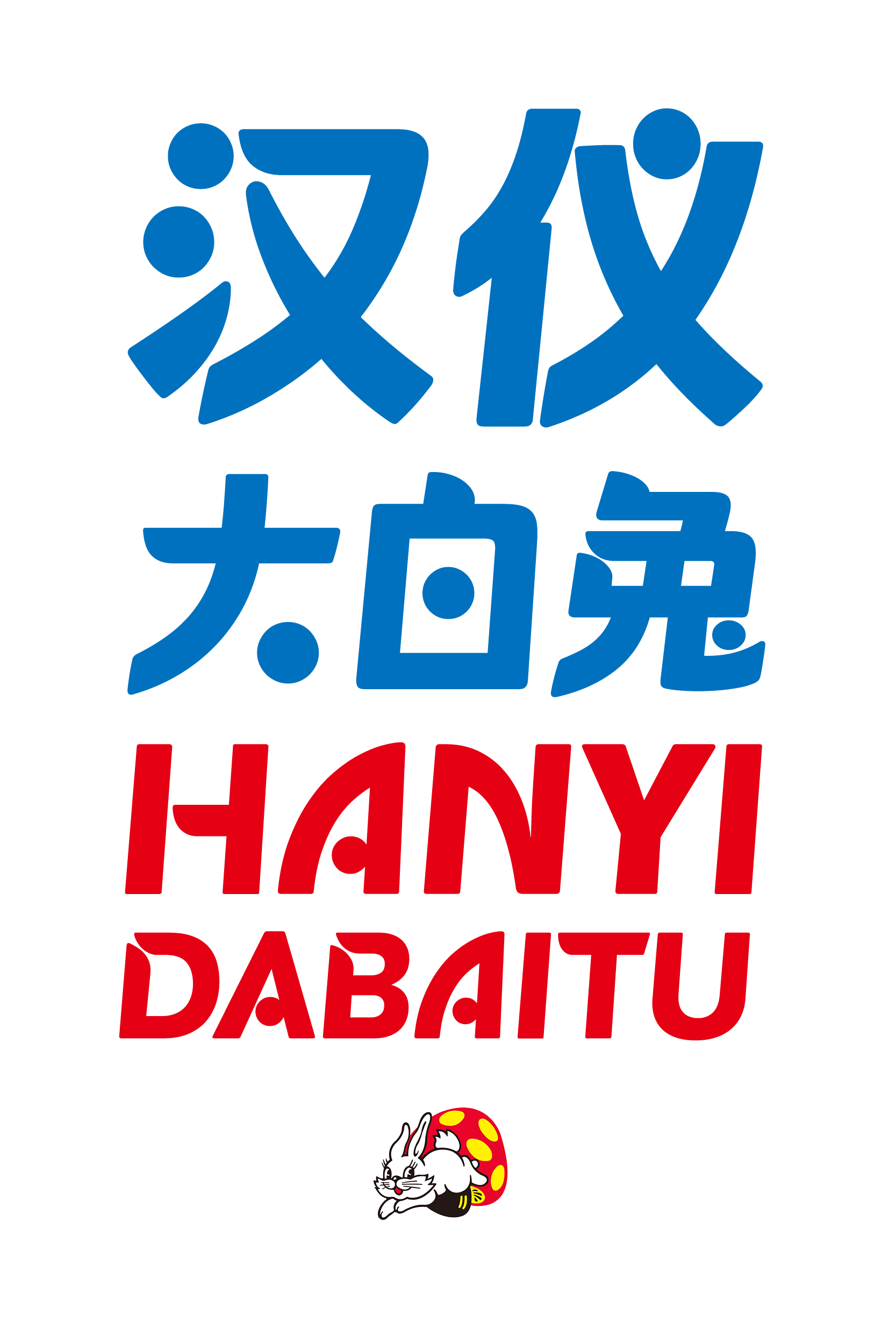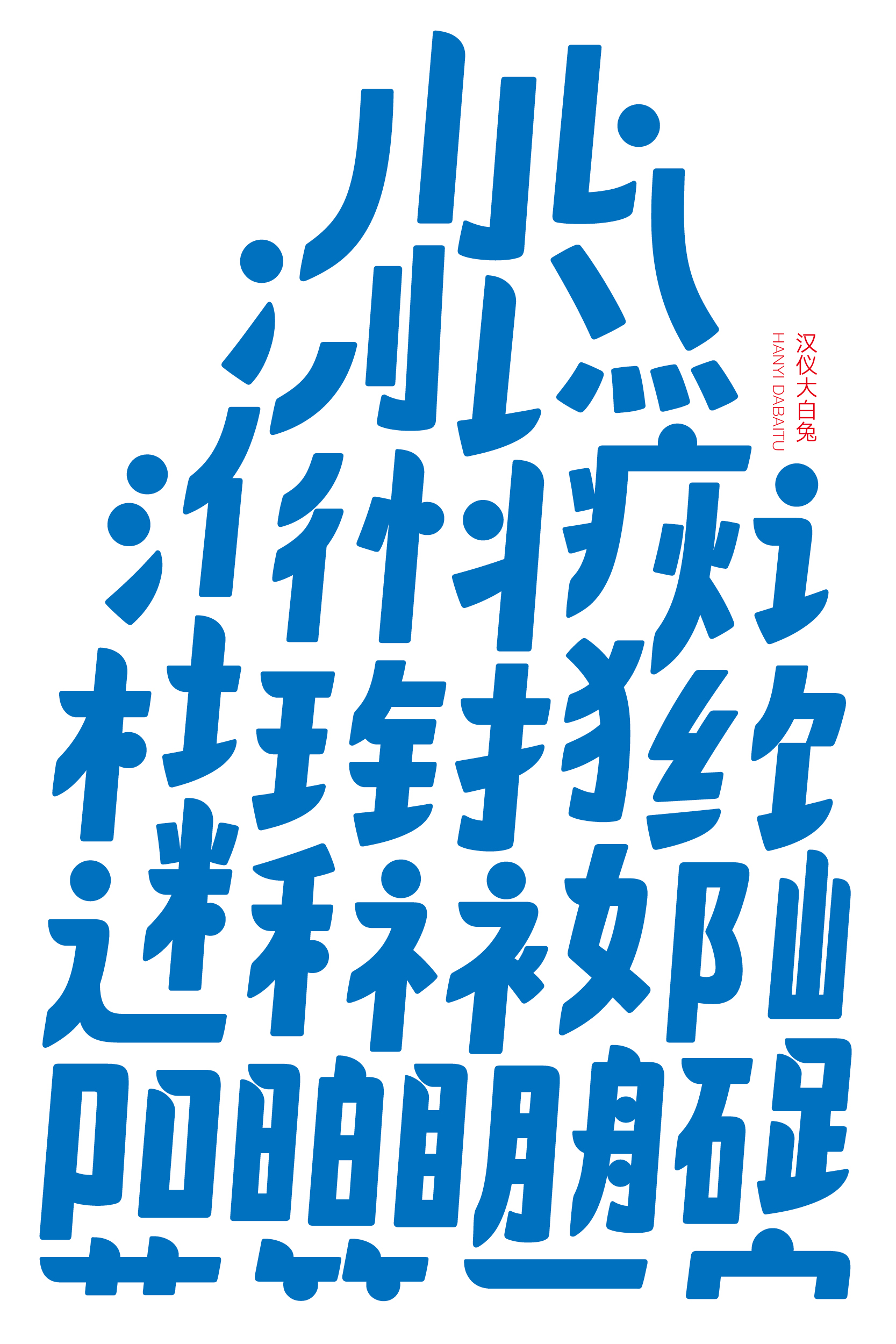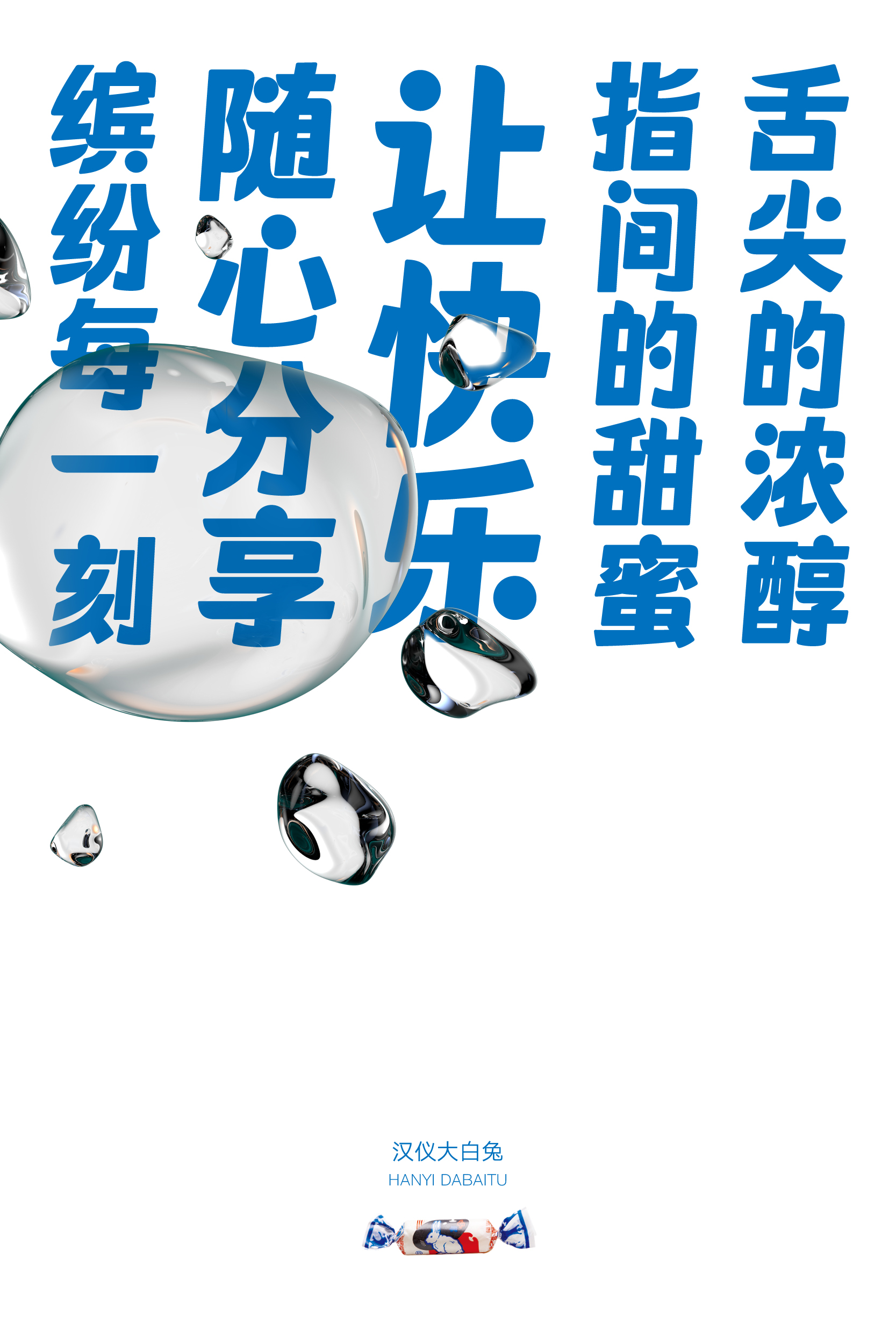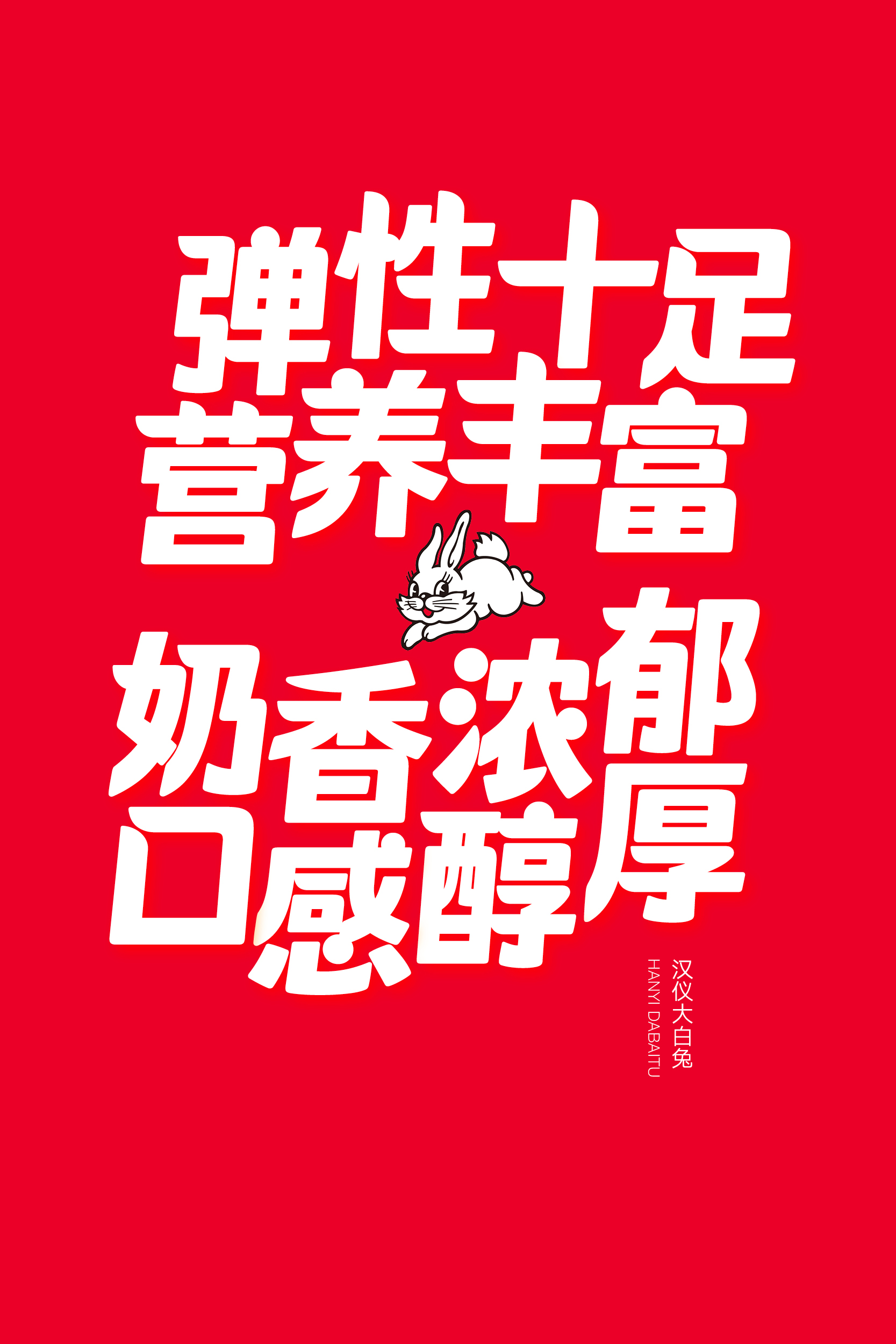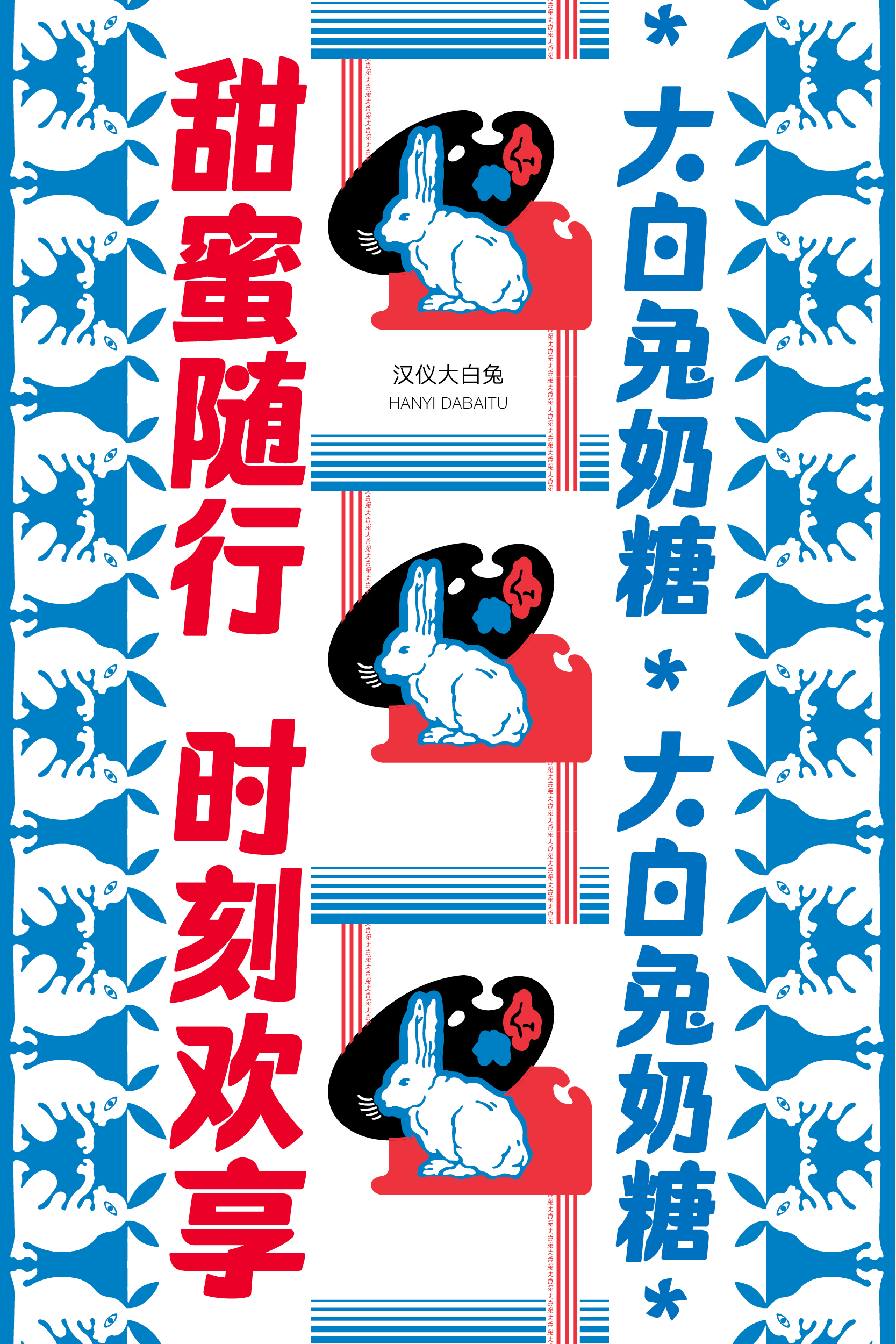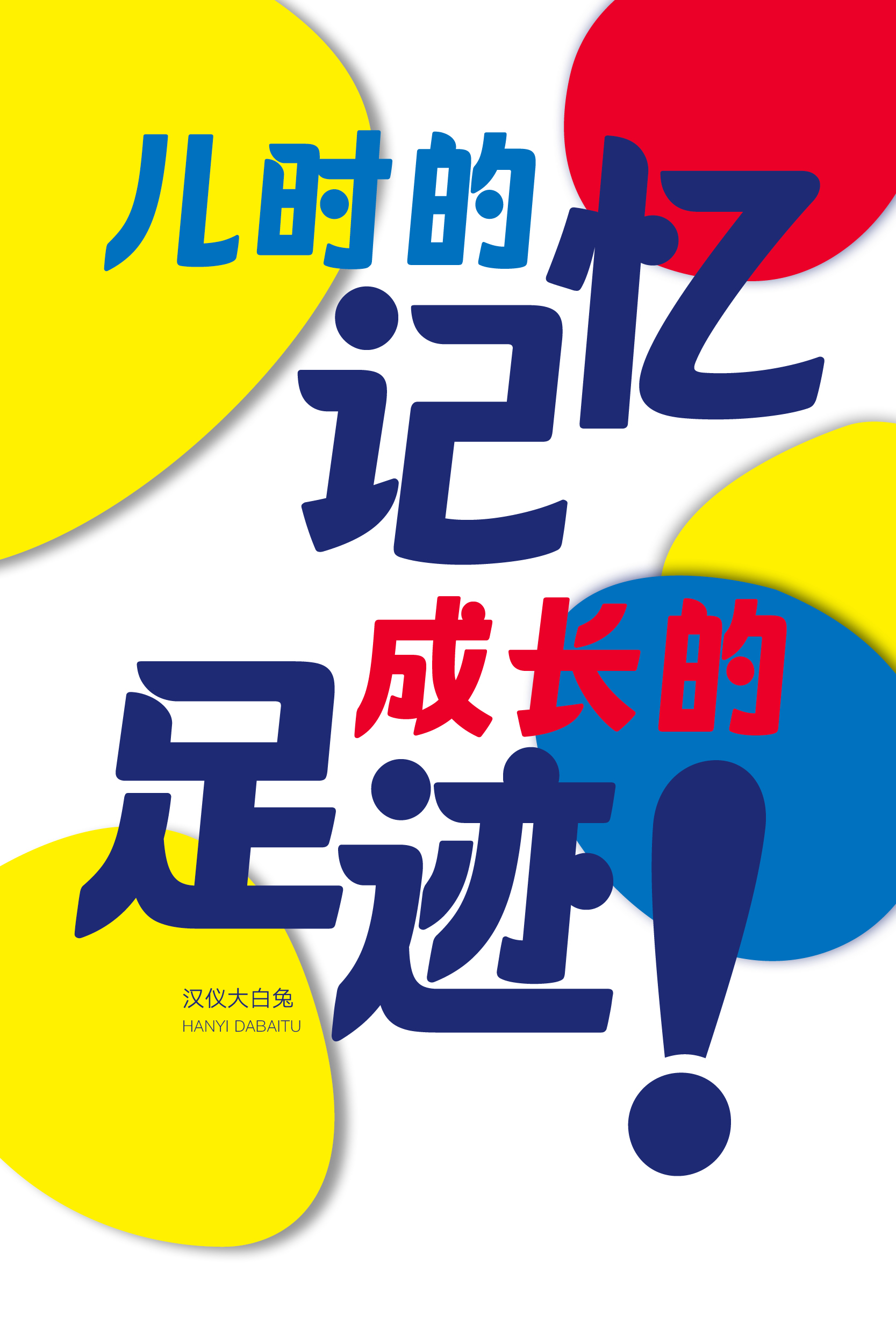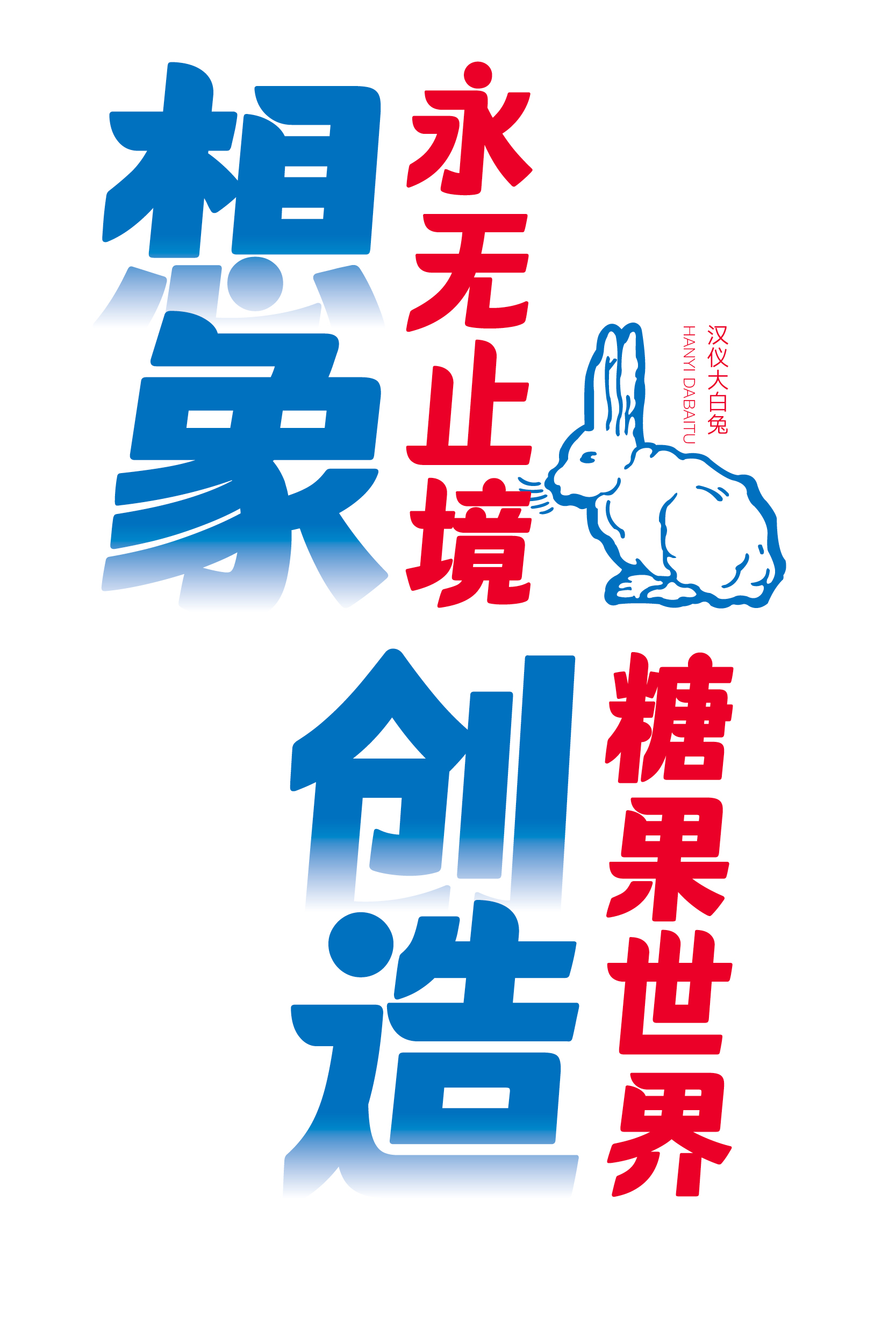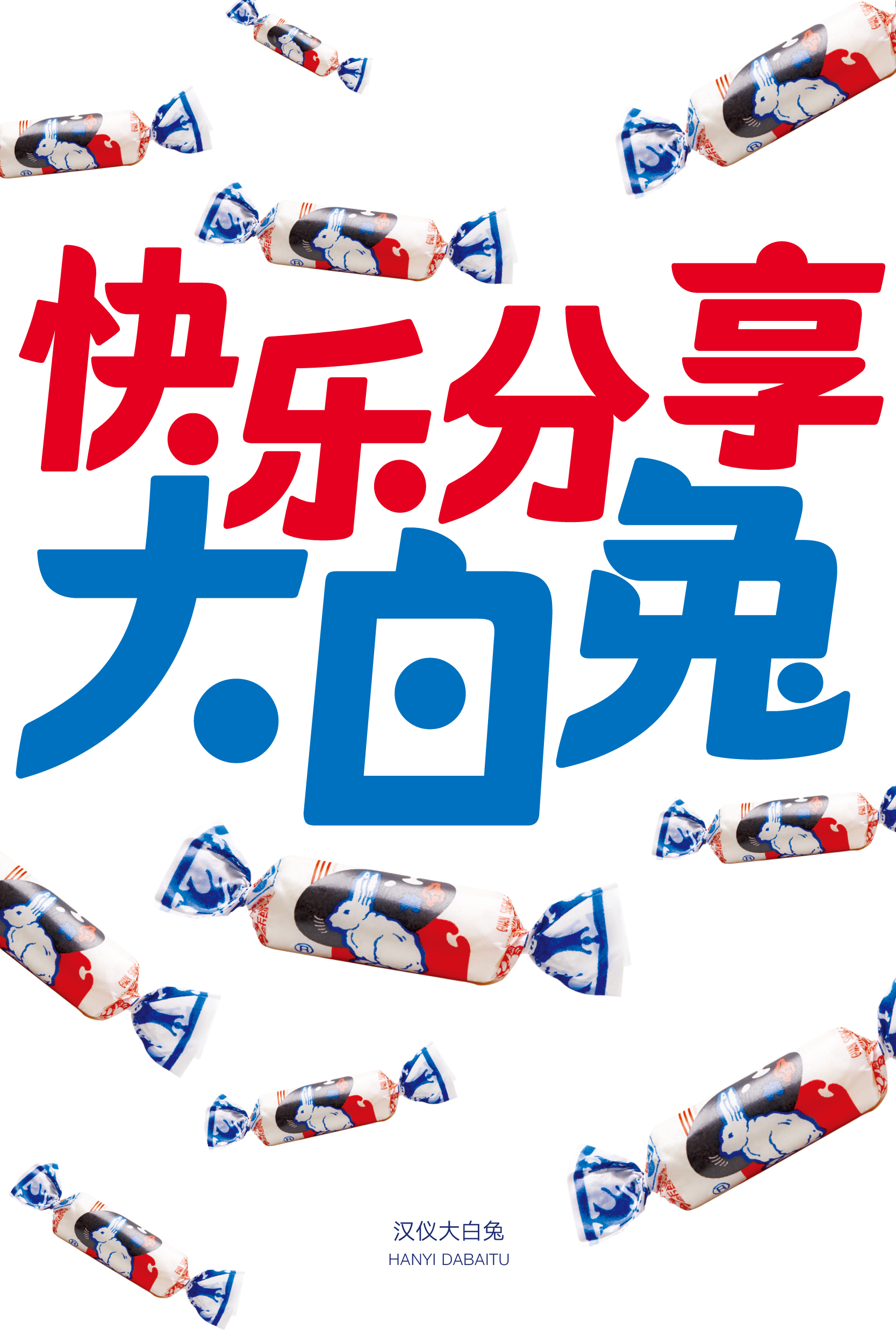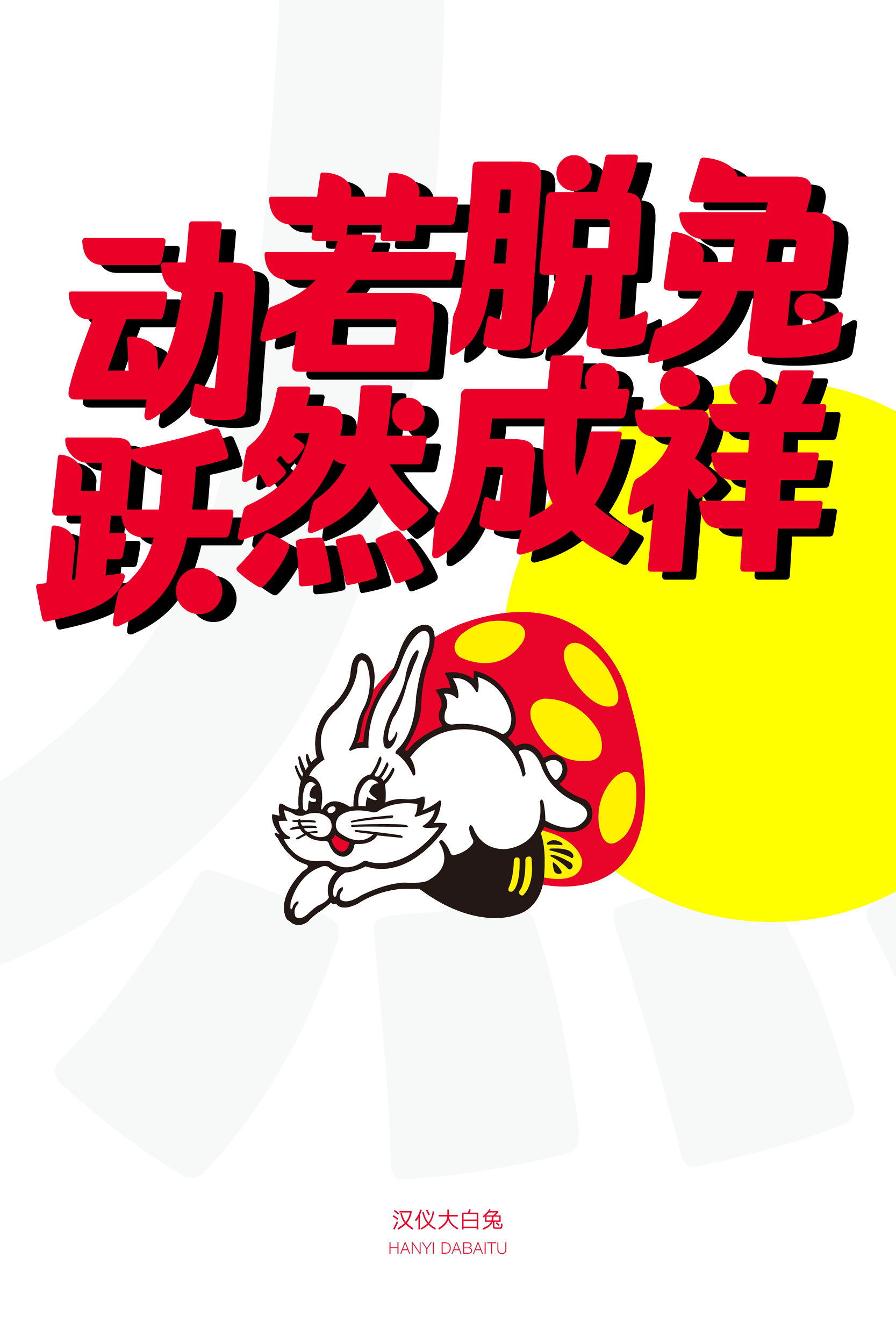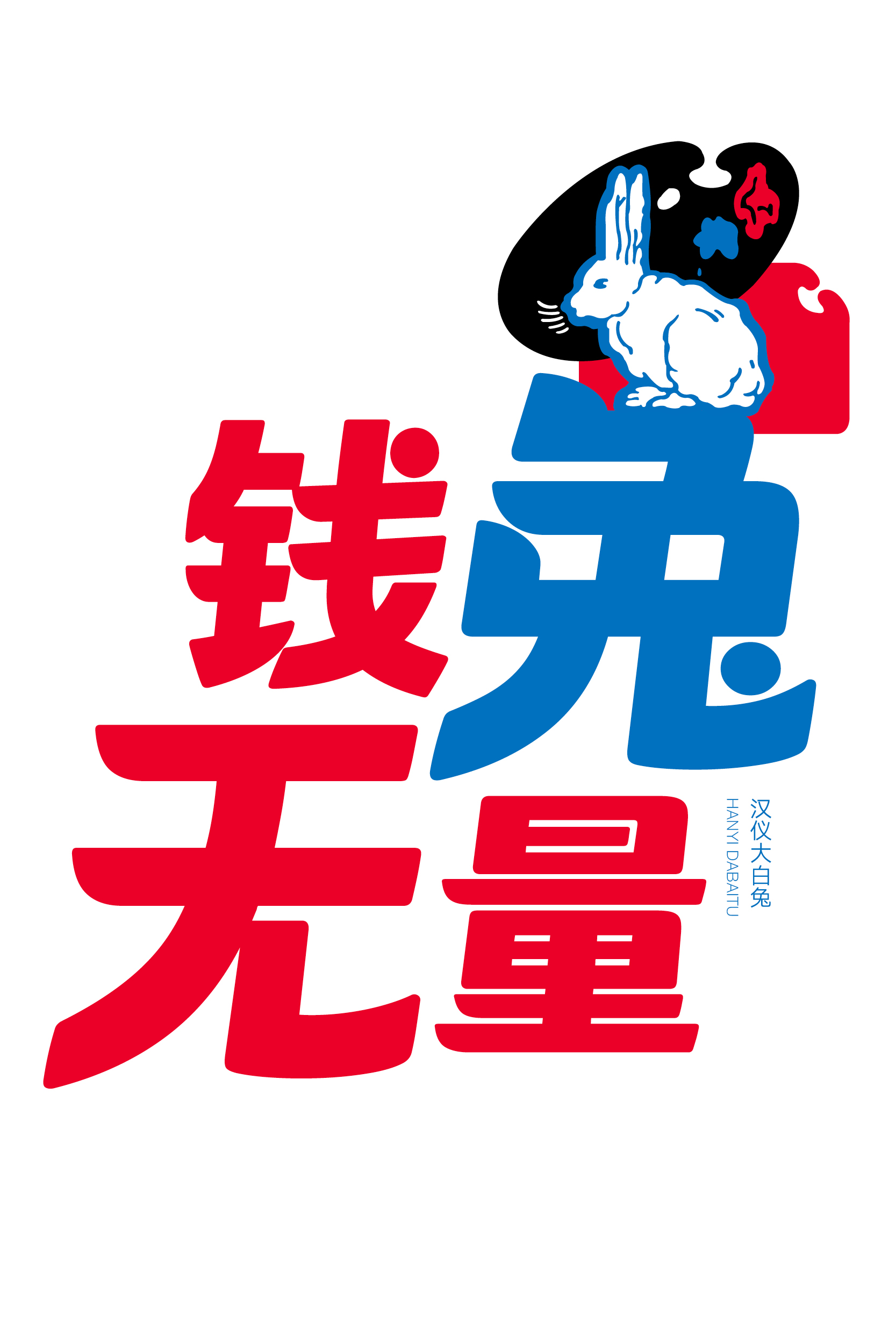
大白兔奶糖联合汉仪字库推出汉仪大白兔W字体
大白兔奶糖联合汉仪字库推出汉仪大白兔W字体,这款字体结构工整、笔画清晰,兼顾美观与易读性,适用于标题、正文、海报、包装、LOGO 等多种场景。字形优雅稳定,风格百搭耐看,适配日常排版与创意设计,让文字呈现更舒适、更具质感。大白兔奶糖联合汉仪字库推出汉仪大白兔W字体一笔一画,皆是细节,以均衡的比例、流畅的线条打造舒适视觉体验,字形端正大气,风格简约现代。无论是商业设计、品牌宣传还是日常排版,都能轻松驾驭,让文字更有格调与力量。大白兔奶糖联合汉仪字库推出汉仪大白兔W字体字体下载。
2022年2月,汉仪字库、大白兔和华东理工大学开展了长达一个月的企校合作课程。大白兔团队帮助华东理工大学视觉传达系20级的同学们理解品牌定位、设计需求和字体实际应用场景。来自汉仪字库的资深字体设计师们教授字体设计的历史、基础知识、设计方法、不同风格字体设计案例、软件应用、提案汇报等专业知识。以大白兔品牌的字体设计为课题,让同学们体验到字体定制设计的流程,提升设计实践技能。在结课汇报中,每位同学都获得了来自大白兔团队和汉仪字库团队的点评和建议。这次课程体现了汉仪字库和大白兔的社会责任感,是企业协助教学、回馈社会的方式之一。
在众多学生和专业设计师的方案比对后,由李晓静设计的汉仪大白兔脱颖而出。汉仪大白兔在传承大白兔品牌经典设计元素的基础上,整体风格更加简洁、现代,对大白兔品牌各类产品、包装、广告及体验式销售模式的应用场景均具有普适性。在细节上提升了优质品牌的高级感,符合大白兔品牌稳重大气、生动有亲和力的“中华老字号”品牌形象。以汉字为切入点打造民族ip,讲好民族品牌故事,坚定文化自信自强。
汉仪大白兔沿用大白兔 logo 字中的装饰圆点设计方式,与logo匹配度高、搭配使用和谐统一。
大白兔几代 logo中文字均为斜体,汉仪大白兔也保留了向右倾斜的势。斜体字的设计虽然在布白和排版上增加了整个字库的设计难度,但最终效果也让字体更有动感、活力、有记忆点。该字体字形方正,有优质标题字的块面感,排版灰度均衡、整齐易读。